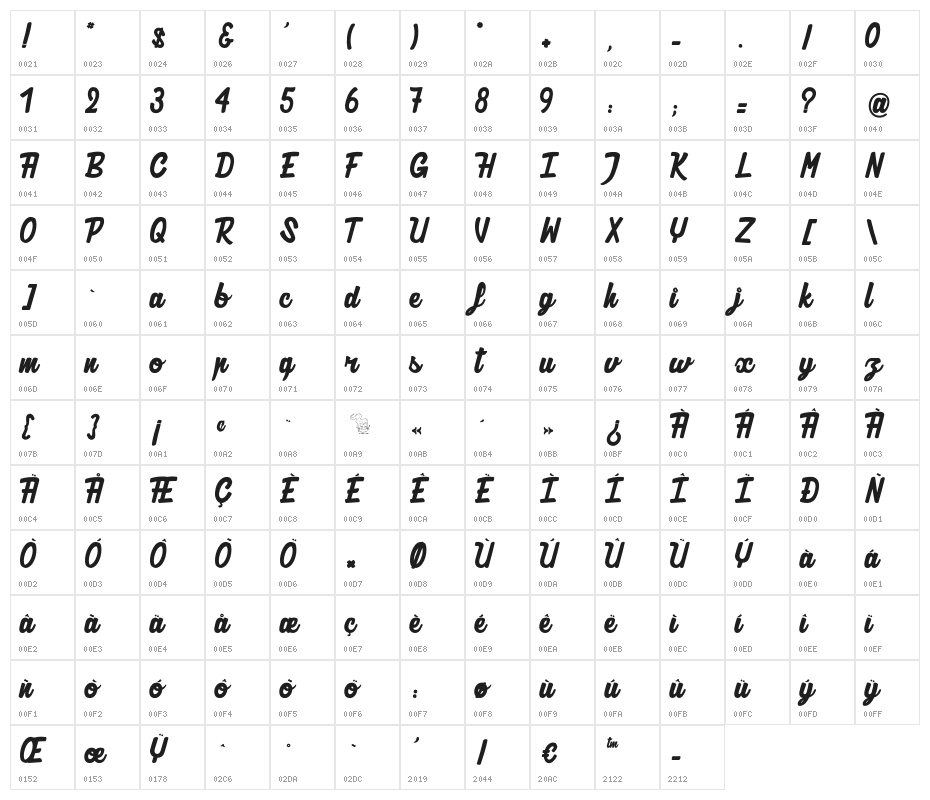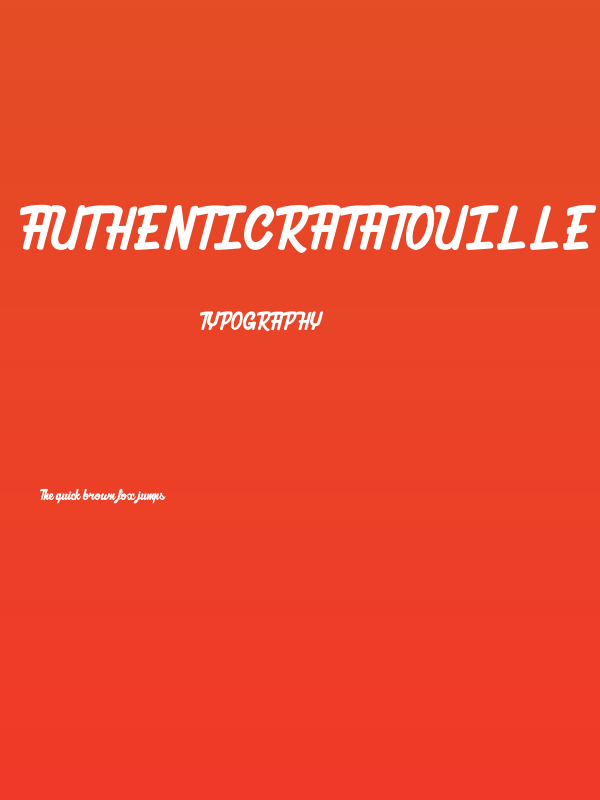
AuthenticRatatouille Font
| Proiecte propuse | Ideal for branding, headlines, posters, and creative projects that require a lively and engaging typeface. |